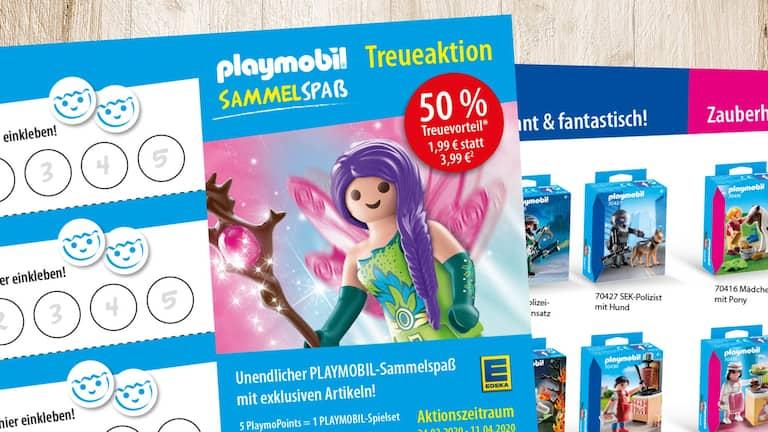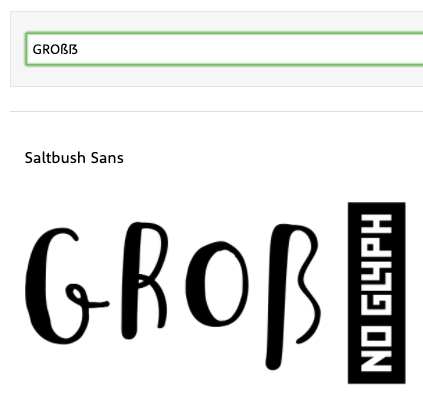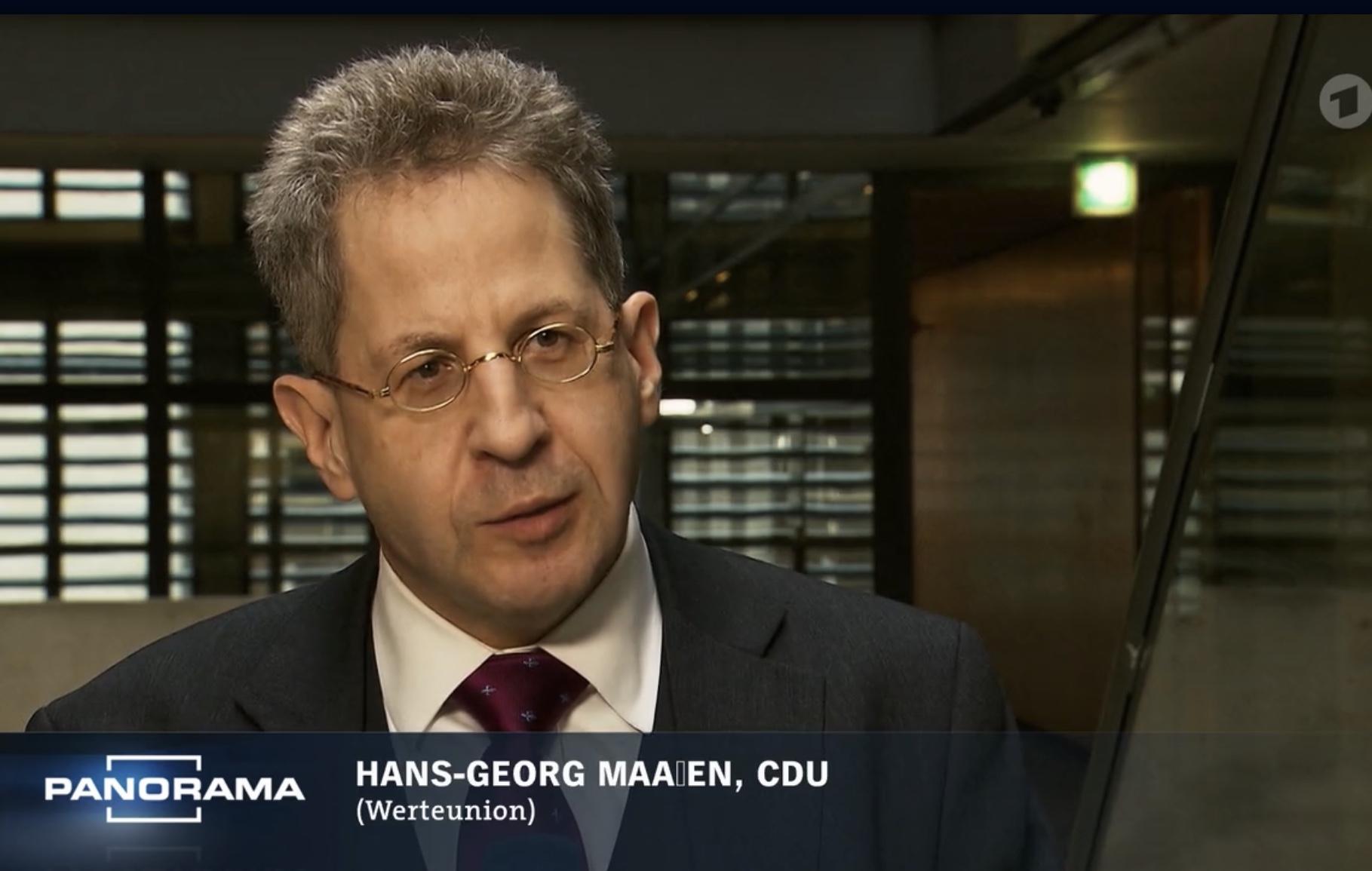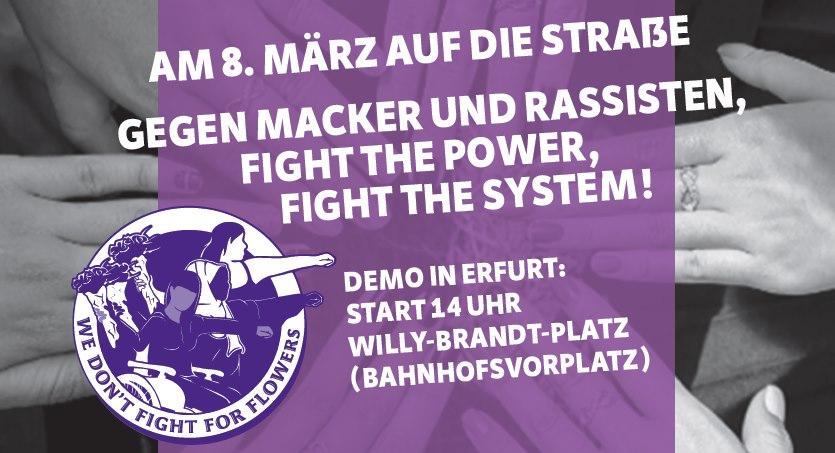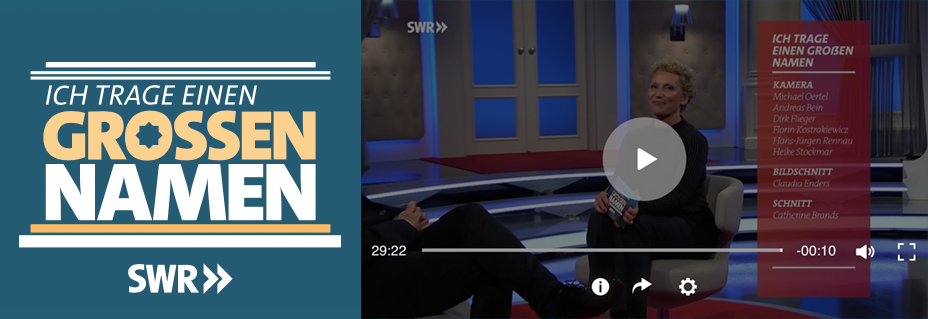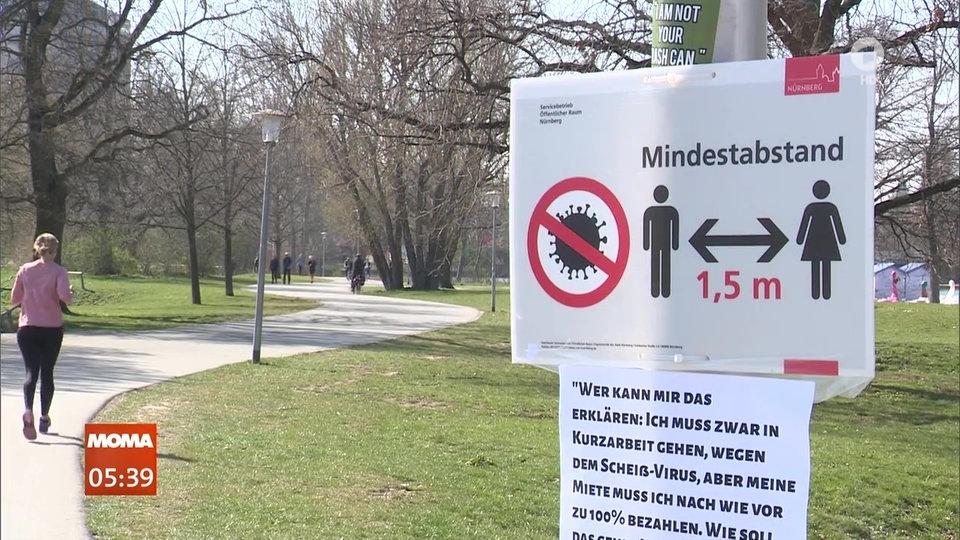
Versaleszett? So’n Quark braucht kein Mensch, dafür gibt es doch so ein Rechteck …
Mit einem Linkseck hätte er bestimmt größere Probleme gehabt :party::hammer:
Muharhar. Mein Abend ist gerettet. :mrgreen:
Passt jedenfalls ganz gut, oder?
... aber die weißen Punzen nerven.
Isses eins?
Ich hab' mal bei einer Insiderin nachgefragt und melde mich, sobald ich etwas höre. Oder sie meldet sich selbst. :-)
Nö.
P.S. Ich bin nicht die Insiderin.
Hätte ich auch wegen der Unterlänge und der Breite nicht vermutet, aus eben jenen Gründen finde ich es auch nicht passend ...
Was sind das denn für Prioritäten: Versal-Eszett statt Genitiv? Wer kann mir das erklären …
Des Virusses wäre doch auch nett. Es gab mal eine Russengrippe. Die hat laut Wikipedia in den Jahren 1977 und 1978  weltweit 500.000–700.000 Todesopfer gefordert. Der gleiche Erreger hat es 1889 auf bis zu einer Million Tote geschafft. Ob die schon Kurzarbeit hatten?
Der Genitiv ist laut Duden heutzutage nicht mehr falsch, nur noch umgangssprachlich. Wegen dem würd ich jetzt keine Szene machen.